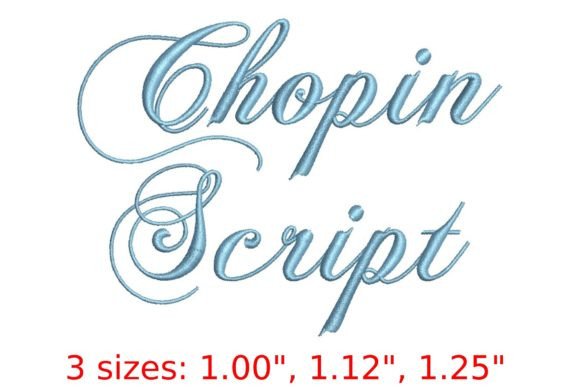
Chopin Script Embroidery Font
Поиск подходящих элементов дизайна может быть сложным, но Chopin Script Embroidery Font предлагает исключительную коллекцию, которая мгновенно улучшит вашу работу.
Созданный с высокой точностью, Chopin Script Embroidery Font предоставляет чистые векторы, плавную типографику и коммерческую лицензию для вашего спокойствия.